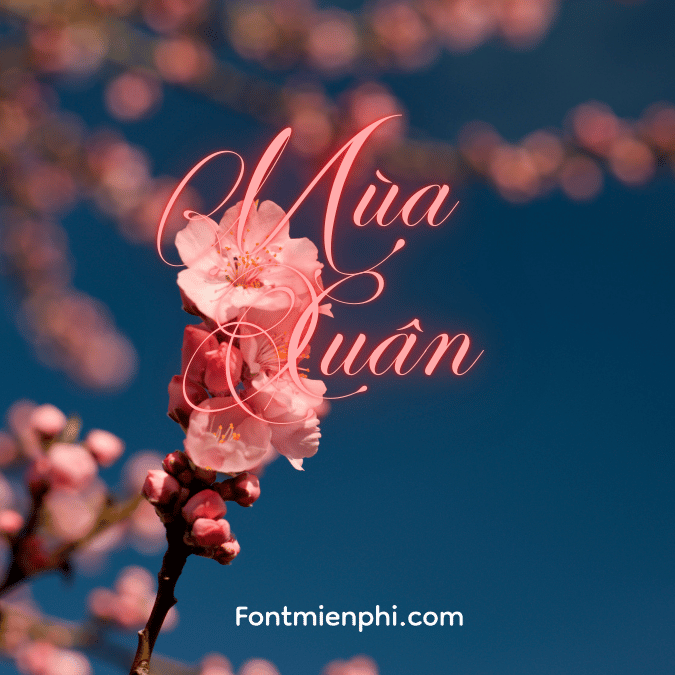
Font Việt hóa 1FTV VIP Perfecto Calligraphy ,Font tết
Font Việt hóa 1FTV VIP Perfecto Calligraphy
Font 1FTV VIP Perfecto Calligraphy là một kiểu chữ nghệ thuật, mang đậm tính chất thư pháp. Dưới đây là một số điểm nổi bật về font này:
1. Phong cách thiết kế: Font này có thiết kế mềm mại, uyển chuyển với các nét chữ tinh tế, tạo cảm giác thanh thoát và sang trọng. Sự kết hợp giữa các đường cong và góc cạnh giúp font trở nên nổi bật hơn.
2. Sự đa dạng: 1FTV VIP Perfecto Calligraphy thường được sử dụng trong các sản phẩm in ấn như thiệp mời, logo, hoặc các tài liệu cần tính thẩm mỹ cao. Đây là một lựa chọn tuyệt vời cho những ai muốn tạo ra ấn phẩm độc đáo và thu hút.
3. Hỗ trợ tiếng Việt: Font này được Việt hóa đầy đủ, bao gồm tất cả các ký tự cần thiết để viết tiếng Việt, đáp ứng nhu cầu sử dụng của người Việt Nam.
4. Ứng dụng: Rất phù hợp cho các dịp lễ hội, đám cưới, hoặc những sự kiện cần sự trang trọng. Đặc biệt, nó cũng có thể được sử dụng trong thiết kế đồ họa số.
5. Cảm xúc: Kiểu chữ này không chỉ đơn thuần là một phương tiện truyền đạt thông tin mà còn mang đến cảm xúc và sự sáng tạo qua từng nét chữ.
Font 1FTV VIP Perfecto Calligraphy chắc chắn sẽ là một lựa chọn thú vị cho những ai yêu thích cái đẹp trong từng chi tiết.